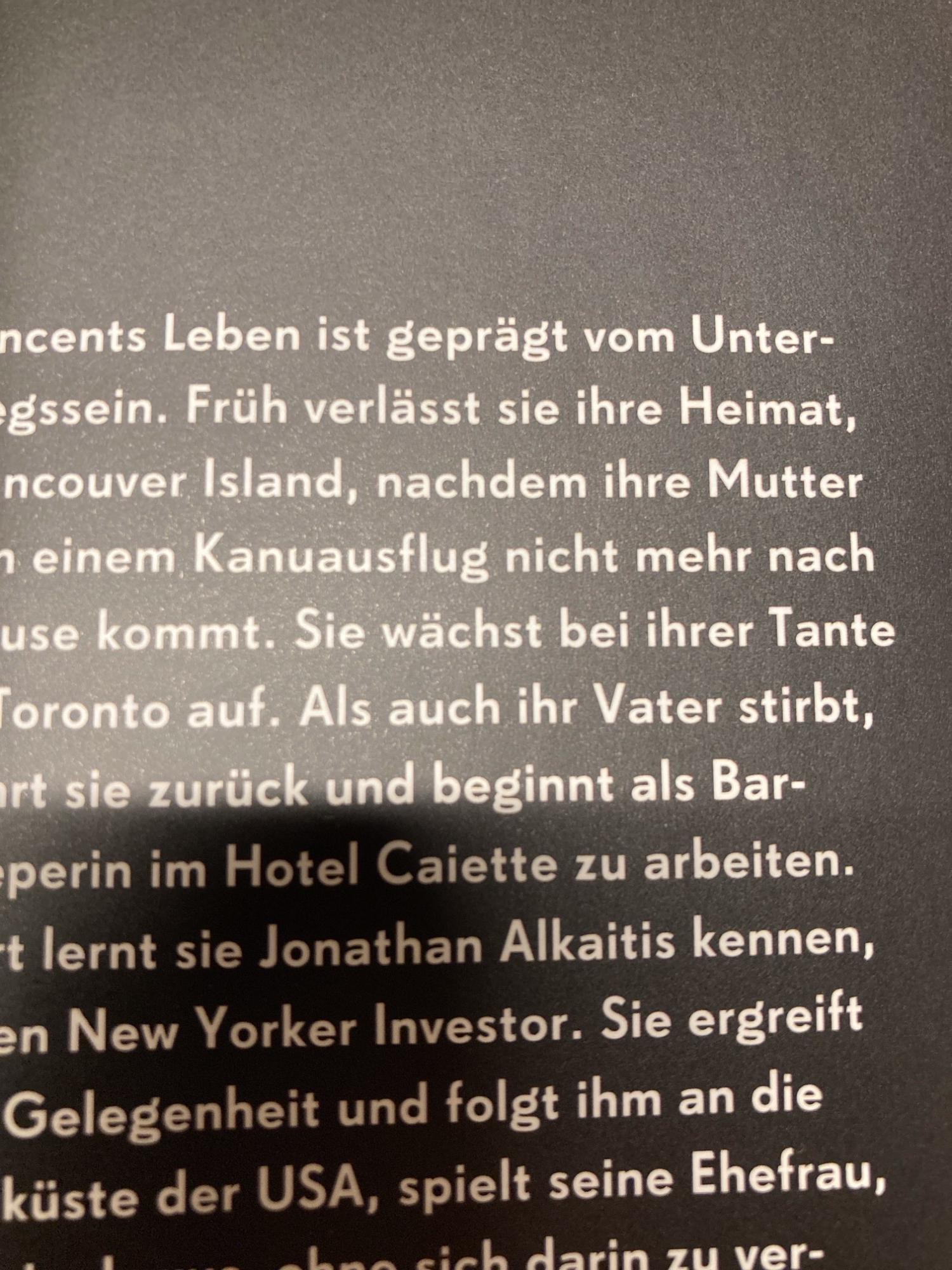
Grotesque Schrift gesucht von Bucheinband (Glashotel)
ich suche die verwendete Schrift auf dem Einband des Buches GLASHOTEL. Anbei ein Foto vom Einbandstext.
Die Brandon Grotesque oder Glarika ist es nicht. Besonders auffällig ist das kleine g.
Das ist mit hoher Wahrscheinlichkeit die FF Super Grotesk. Ich habe die Schrift selbst nicht, gehe aber mal davon aus (siehe Galeriebilder), dass es Alternativformen bei »a« und »g« gibt.